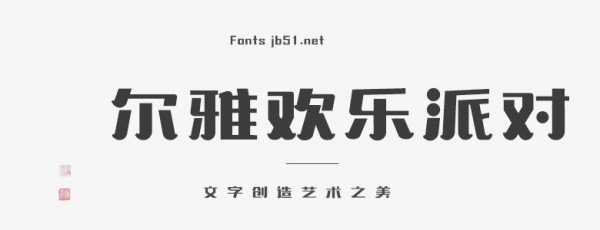
爾雅歡樂派對(duì)是一款簡(jiǎn)約漂亮的卡通可愛創(chuàng)意字體,適合應(yīng)用于藝術(shù)設(shè)計(jì)、平面宣傳設(shè)計(jì)、網(wǎng)頁設(shè)計(jì)、書法字體,海報(bào)設(shè)計(jì)等領(lǐng)域,歡迎喜歡這款字體的朋友下載使用,歡迎喜歡這款字體的朋友下載收藏。